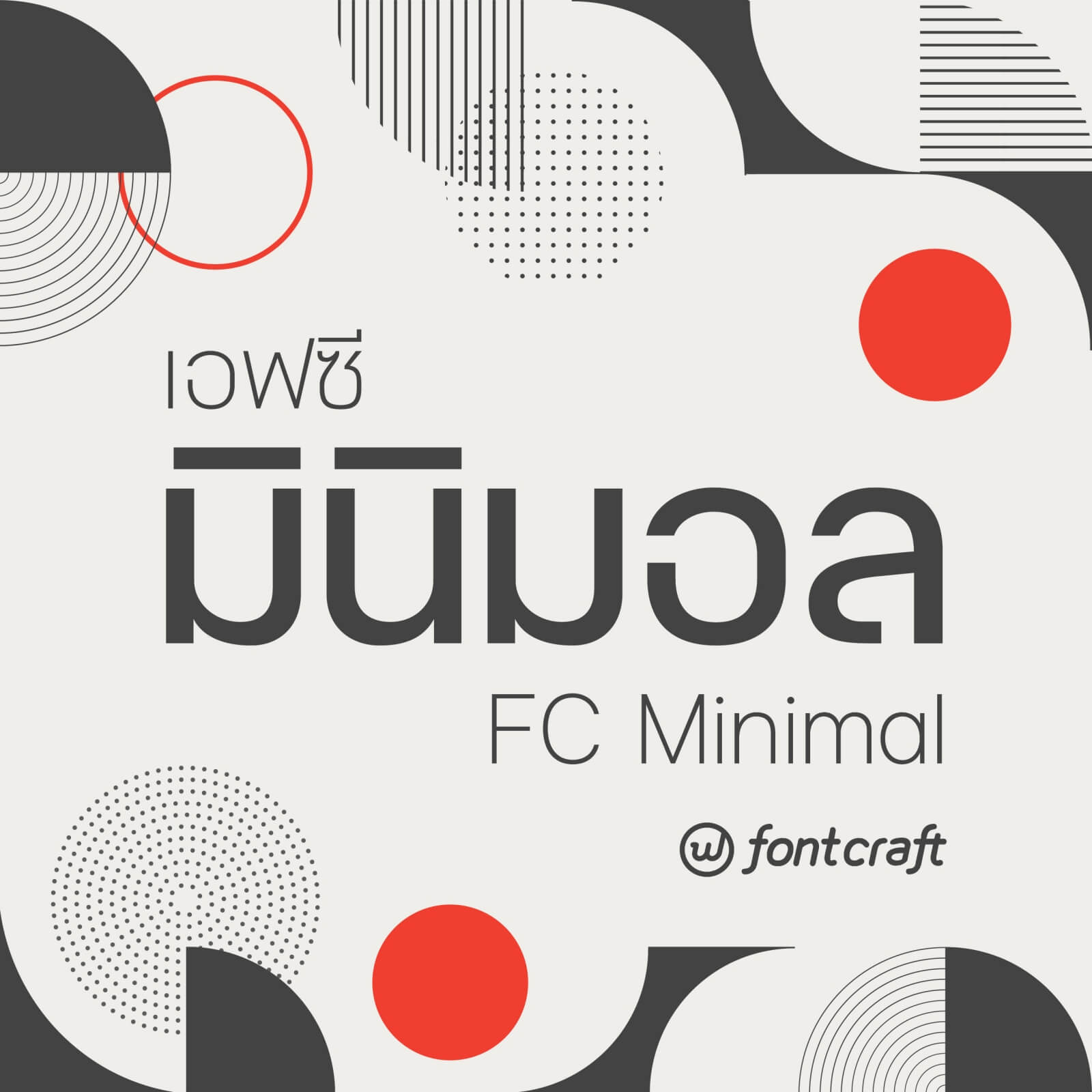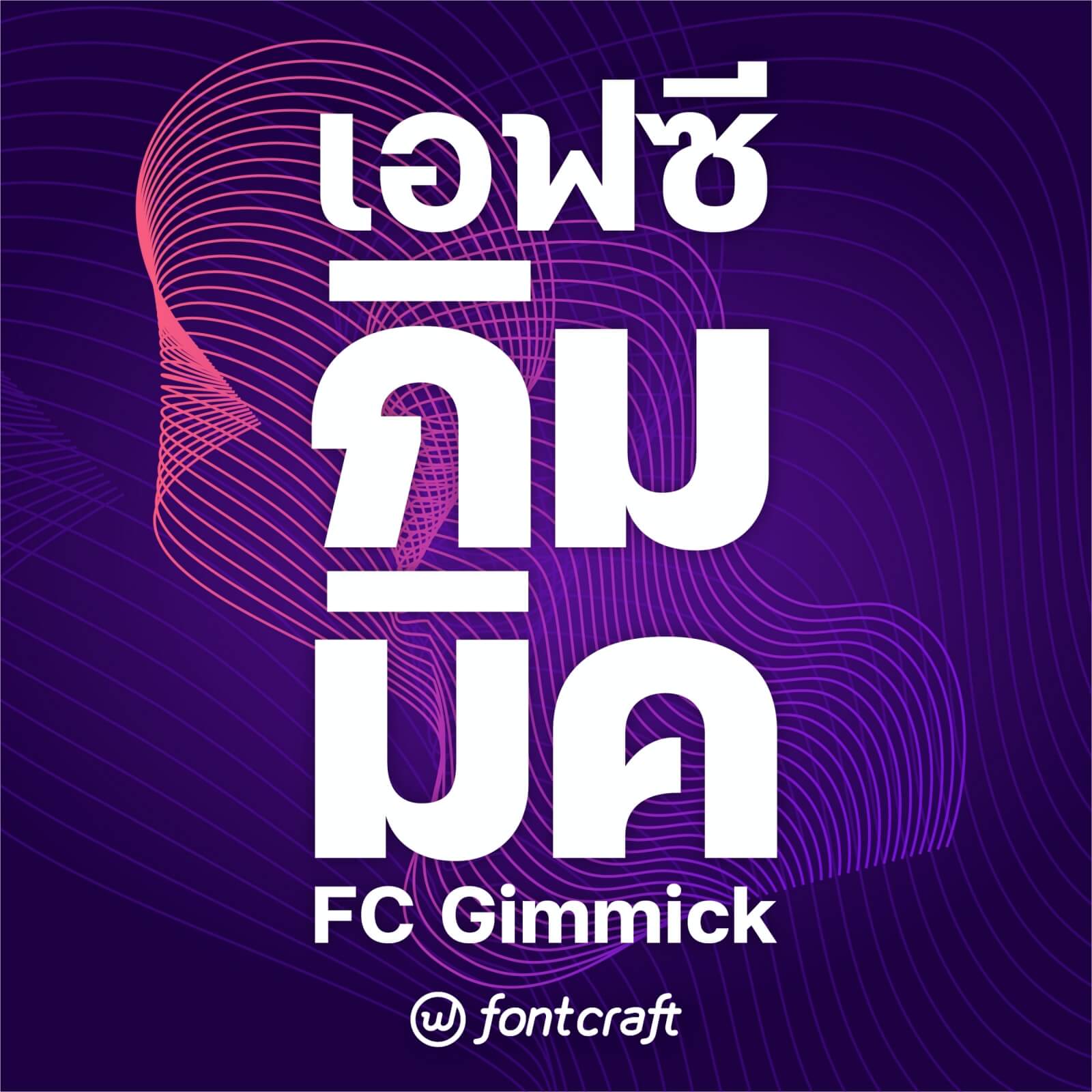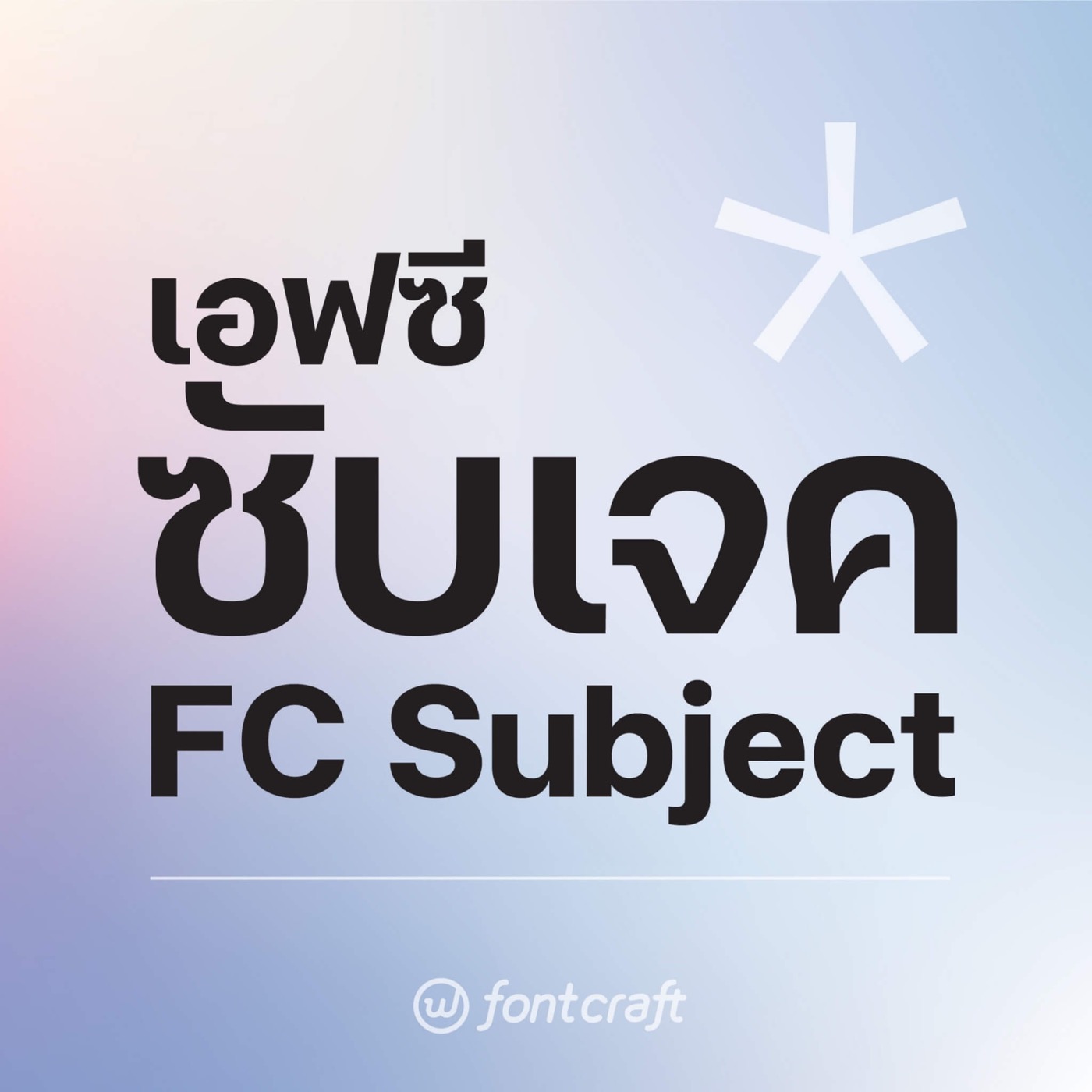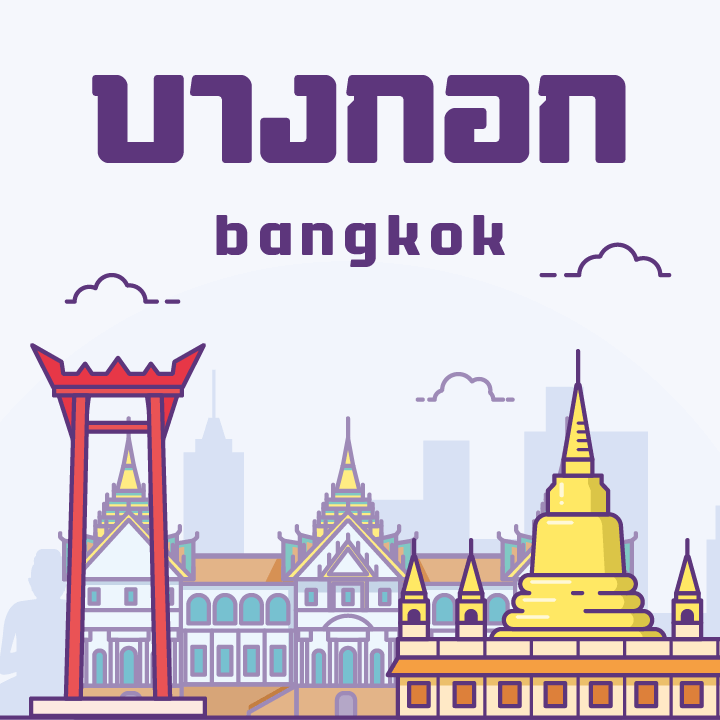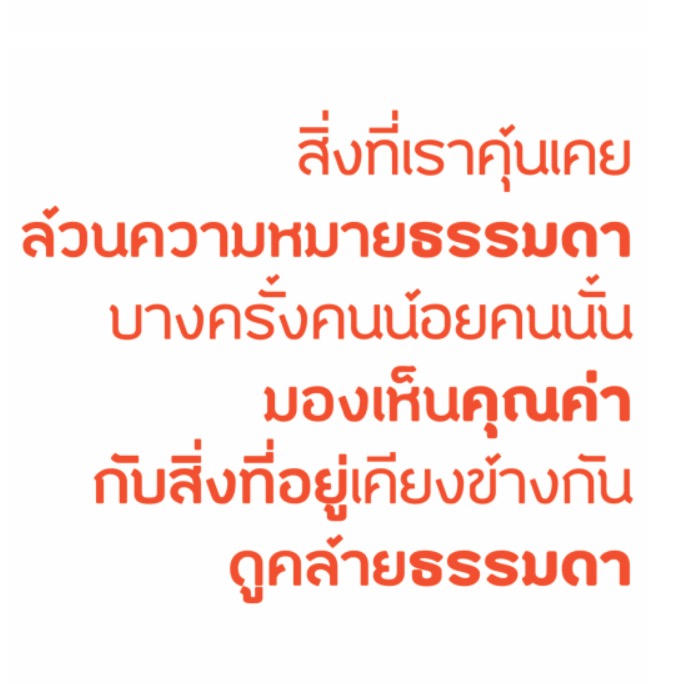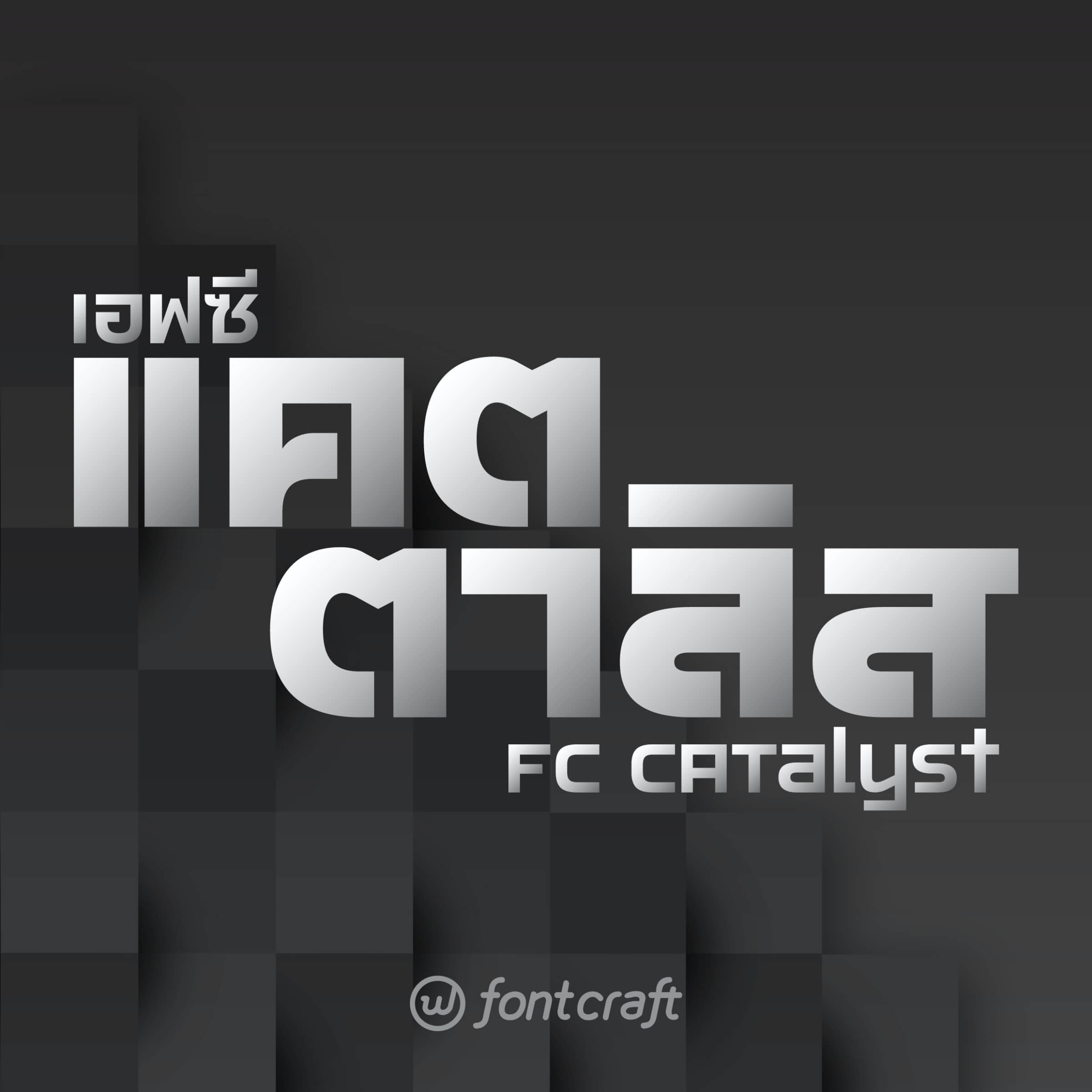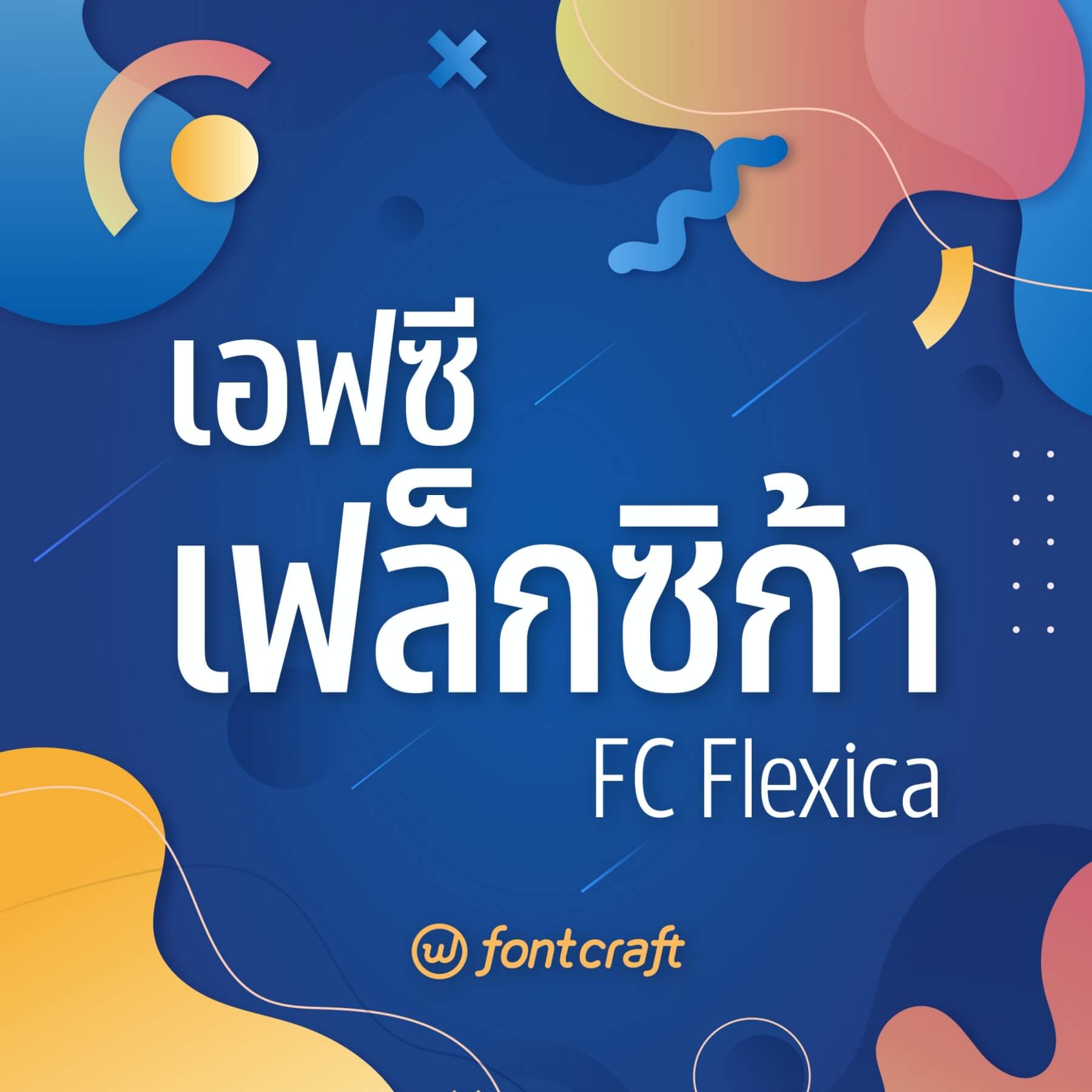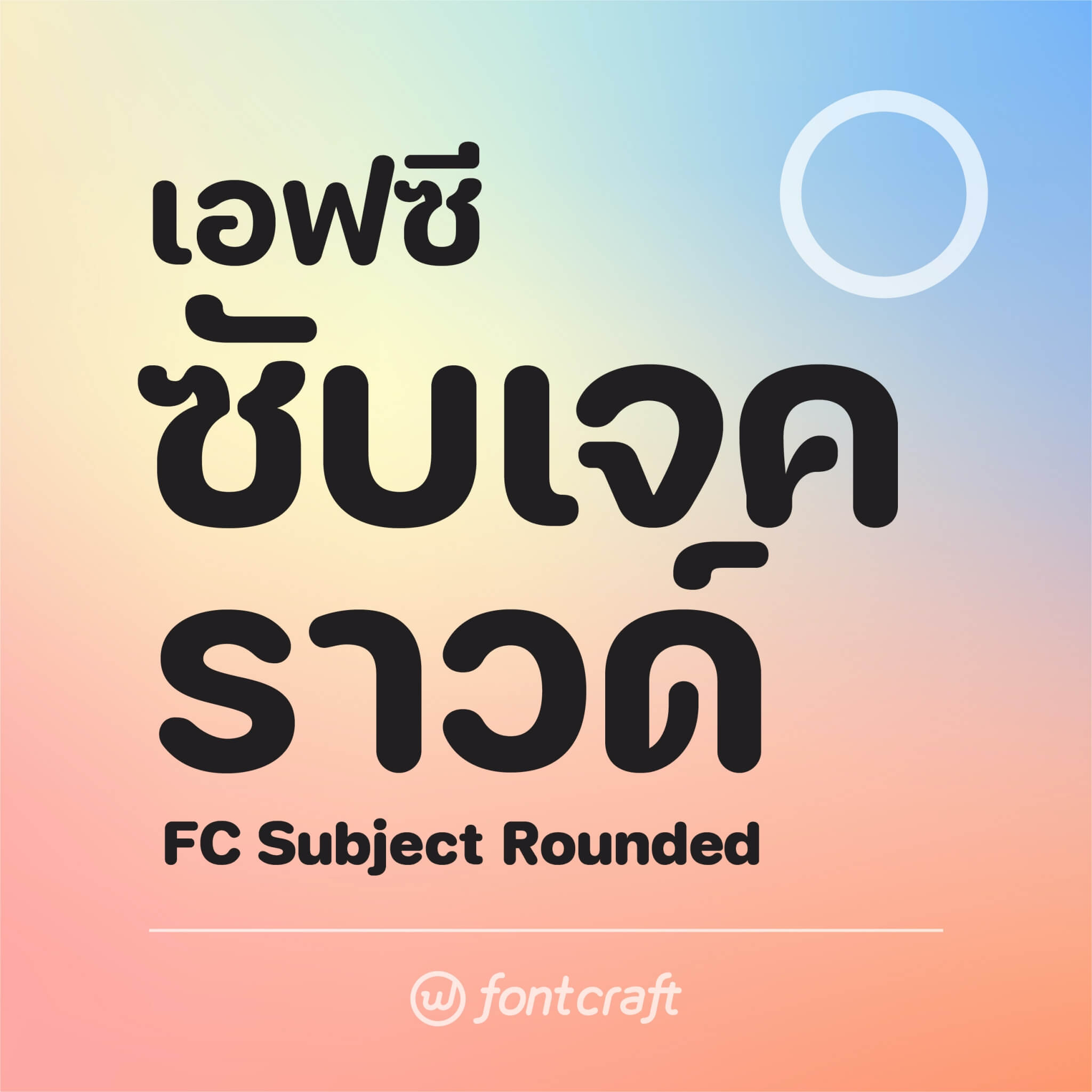
แนะนำ 8 ฟอนต์สไตล์โมเดิร์น ไม่มีหัว แต่อ่านง่าย สบายตา จากฟอนต์.com
สำหรับครั้งนี้ทีมงานได้เลือกฟอนต์แนวโมเดิร์น เน้นแบบไม่มีหัว อ่านง่ายสบายตา มาแนะนำไว้ให้หลายคนนำไปทำงานนำเสนอ งานอาร์ตเวิร์ต ตกแต่งโน้ตให้สวยน่ารัก ๆ ทีมงานได้รวบรวมฟอนต์ไทย จากเว็บไซต์ ฟอนต์.คอม มาแนะนำให้ดาวน์โหลดกันค่ะ
แนะนำ 8 ฟอนต์สไตล์โมเดิร์น ไม่มีหัว แต่อ่านง่าย สบายตา จากฟอนต์.com
1. เอฟซี มินิมอล (FC Minimal)
2. บางกอก (bangkok)
3. Pind (ปิ่น)
4. เอฟซี แคตตาลิส (FC Catalyst)
5. เอฟซี กิมมิค (FC Gimmick)
6. เอฟซี เฟล็กซิก้า (FC Flexica)
7. เอฟซี ซับเจค (FC Subject)
8. เอฟซี ซับเจค ราวด์ (FC Subject Rounded)